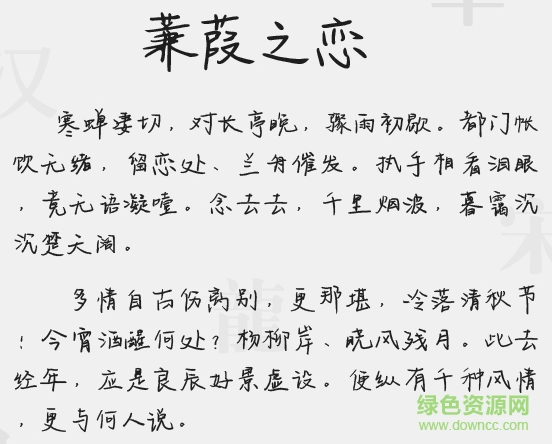
蒹葭之戀字體ttf
蒹葭之戀字體是一款干凈有情懷的藝術(shù)字體,字跡清晰不潦草,很有手寫體的認(rèn)真感和淡雅樸質(zhì)的視覺體驗(yàn),如果你喜歡,就快來綠色資源網(wǎng)下載吧!
蒹葭之戀字體ttf特色
本字庫是在國家標(biāo)準(zhǔn)簡體字庫GB2312所包含6763漢字的基礎(chǔ)上,又增加了近200常用字,已經(jīng)覆蓋了大陸99.75%的漢字使用頻率,足以滿足日常需求。
蒹葭之戀字體
蒹葭之戀手寫字體制作
首先設(shè)計(jì)手寫字稿,然后手寫字稿數(shù)字化。
手寫字稿設(shè)計(jì)過程
打格,畫出字面框和字身框
用單線勾勒出字體骨骼
根據(jù)骨骼勾畫輪廓
借助尺規(guī)工具修正筆畫結(jié)構(gòu)
勾邊緣線
填黑
整體修正